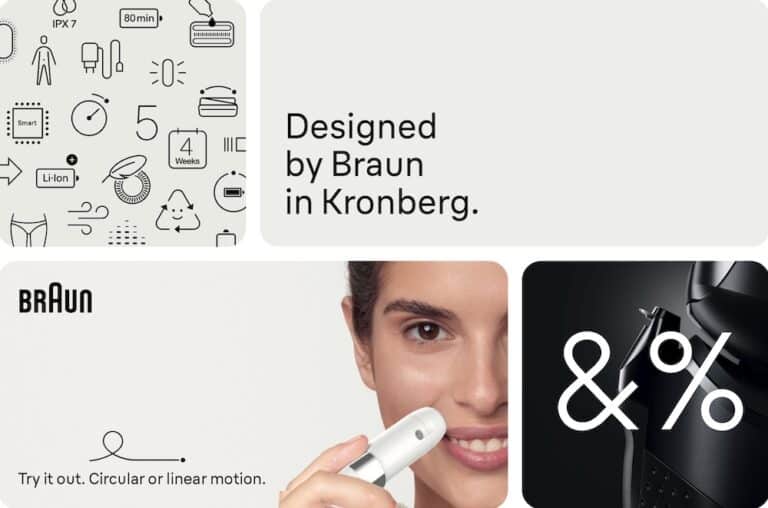
Neue Schrift für Braun
Braun Linear ersetzt die bislang verwendete Neue Helvetica als Corporate Font der Braun GmbH.
Der Name Linear ergibt sich aus dem geringen Strichstärkenkontrast. Entwickelt haben die Schriftfamilie Typedesigner Ludwig Übele und Stefan Dziallas, der mit seinem Bremer Büro iconwerk vor allem custom icons gestaltet.
»Es war schon sehr aufregend und auch ein bisschen beängstigend, den Corporate Font eines Unternehmens wie Braun mit seinem wichtigen Designerbe zu überdenken,« sagt Stefan Dziallas. Sein Typografieprofessor Eckard Jung studierte an der hfg ulm und lernte von Otl Aicher. Das Design vieler Braun-Geräte orientiere sich an den Designprinzipien der Ulme Schule. So schließe sich ein Kreis.
Braun Linear ist eine schlanke, nützliche, freundliche, deutsche und moderne Schrift, die sich klar an den Braun-Design-Gesetzen Einfachheit, Ordnung und Harmonie orientiert und die Kommunikationsmöglichkeiten des Unternehmens erweitert und bereichert.
Braun Linear ist eine schlanke, nützliche, freundliche, deutsche und moderne Schrift, die sich klar an den Braun-Design-Gesetzen Einfachheit, Ordnung und Harmonie orientiert
Braun Uhr mit neuer Schrift Braun-Gerät: Einsatzbeispiel von neuer Schrift Braun Linear Schnitte Thin, Light, Regular, Medium und Bold Dieter Rams Zitat in Braun Linear und Bold Dran Gerät und Design Zitat in Braun Linear Bold